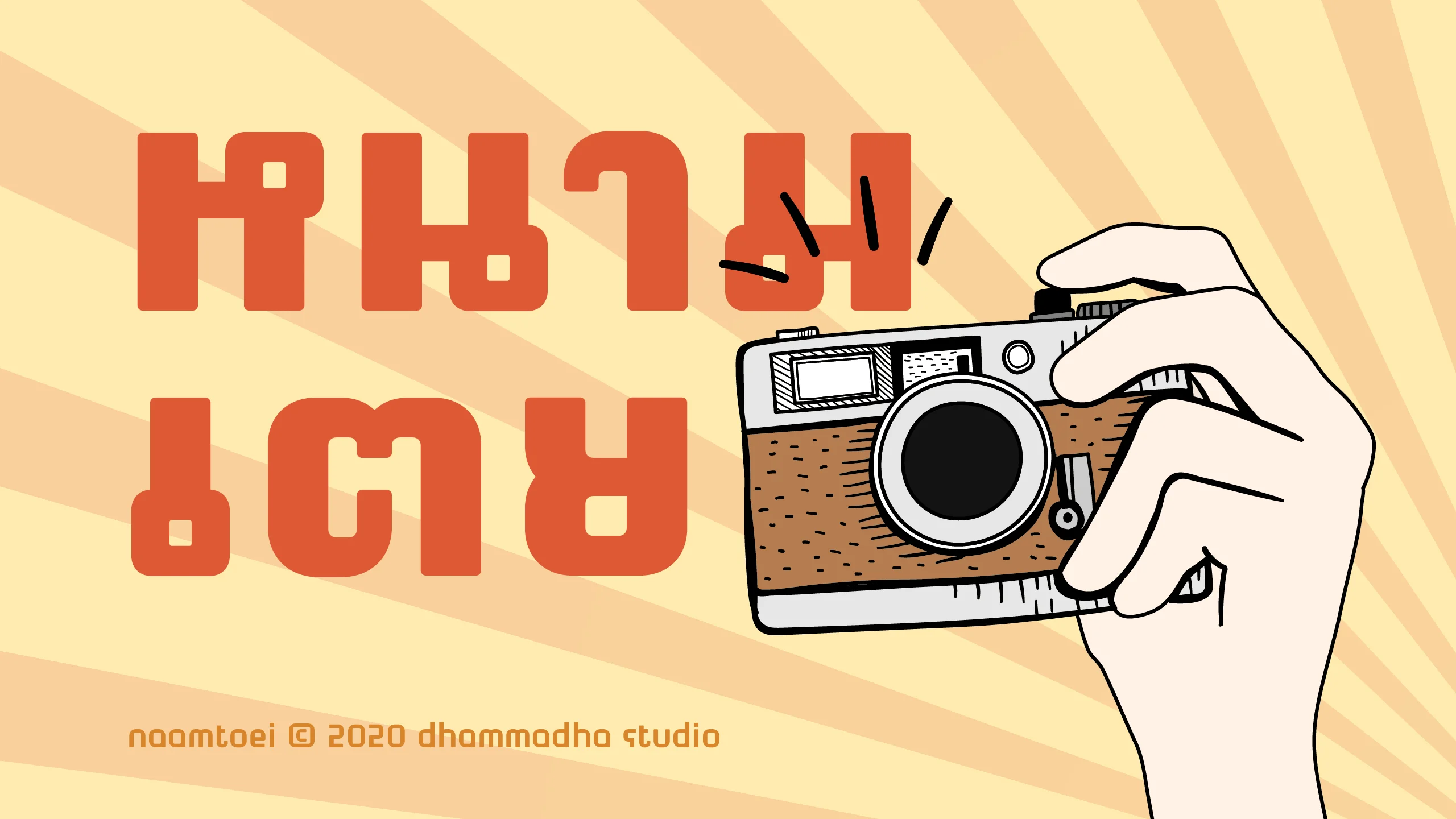
"หนามเตย | naamtoei" คือชุดอักษรที่สะท้อนลายเซ็นการออกแบบในสไตล์ DHAMMADHA STUDIO ได้อย่างชัดเจน ด้วยรูปลักษณ์ที่เน้นความอ้วนตันและสัดส่วนที่ดูแน่นหนา ให้ความรู้สึกย้อนยุคนิดๆ แต่ยังคงความร่วมสมัยไว้อย่างลงตัว ตัวอักษรแต่ละตัวถูกขัดเกลาให้มีจังหวะที่ดูเก๋าและมีชั้นเชิง มอบบรรยากาศที่เปี่ยมด้วยเรื่องราวของวันวานแต่ยังสื่อสารได้อย่างทรงพลังในโลกดีไซน์ปัจจุบัน เป็นฟอนต์ที่สร้างสมดุลระหว่างความหนักแน่นและความเป็นมิตรได้อย่างมีเสน่ห์ ด้วยบุคลิกที่โดดเด่นสะดุดตาเป็นพิเศษ ฟอนต์ชุดนี้จึงได้รับการออกแบบมาเพื่อทำหน้าที่เป็นฟอนต์ Display สำหรับงานพาดหัว (Headline) ที่ต้องการพลังและความน่าจดจำ ไม่ว่าจะเป็นป้ายโฆษณาที่ต้องการความโดดเด่นสไตล์เรโทร งานสร้างอัตลักษณ์แบรนด์ที่เน้นความเก๋าและน่าเชื่อถือ หรือการจัดวางกราฟิกที่ต้องการความชัดเจน "หนามเตย | naamtoei" จะช่วยเปลี่ยนข้อความพาดหัวธรรมดาให้กลายเป็นงานศิลปะที่ดึงดูดสายตาและสร้างเอกลักษณ์ที่ไม่มีใครเหมือนให้กับผลงานของคุณ